5 款在线艺术字生成器,零基础做高级感标题
艺术字一般是易于辨认、美观有趣、醒目张扬的装饰性字体,经常被用于标题设计或广告设计。想要做出有质感的艺术字,但是苦于不会用专业的设计软件,找到的字体又经常有版权问题。要么就是下载安装的字体效果生硬,调整半天也难以达到想要的氛围感。我特地为大家整理了 5 款免费在线艺术字生成工具,覆盖不同的设计风格和场景,零基础也能一键打造高级感的标题。这些工具我都反复使用过,每款生成器都有各自的优势功能,核心目的都是帮助大家告别繁琐的字体设计,轻松获得满意的艺术字,创作出光彩夺目的作品!
一、字由
字由是一款综合性的字体管理神器,不仅拥有海量正版的艺术字资源,还内置了强大的 AI 工具一键生成艺术字,成为很多零基础用户打造高级感标题的首选工具。
用字由在线生成艺术字的流程非常简单,具体操作如下:
- 进入字体生成页面
在搜索引擎内找到字由官网,也可以点击链接(https://www.hellofont.cn/home)进入官网。在首页上方的导航栏点击【字体工具】-【AI 字体】。
- 按风格筛选艺术字模板
页面内可以看到很多 AI 字体模板,用户通过筛选功能快速定位想要的艺术字。字由的筛选分类非常清晰,可以按照场景(社交媒体、心情签、大广赛、影视文字、游戏美术等)、风格(植物、气球、云雾、毛绒、国风、哥特、科技、霓虹等)、语言(中文、英文)三大类多维度进行筛选。
- 一键生成艺术字并下载
选到一款心仪的艺术字模板之后,点击“做同款”;输入文字内容,点击“立即生成”,30s 之内会自动生成样图同款艺术字,不满意可以重新生成哈。为保证最佳效果,自定义文本字数建议与图片字数一致哦。完成后可直接将艺术字下载为透明背景的 PNG 格式,这样便于后续直接拖拽到其他设计软件中使用。
非常贴心的一点是,字由的 AI 字体模板会定期更新,紧跟当下的潮流趋势及时效性活动,比如五一劳动节前夕就会更新很多对应节日风格的模板。对于新手来说,字由无需掌握任何设计技巧就能生成专业级艺术字,对于资深设计师而言,这些即时更新的模板也会为你提供大量灵感,节省设计成本和时间,是一款全能型的艺术字生成器。
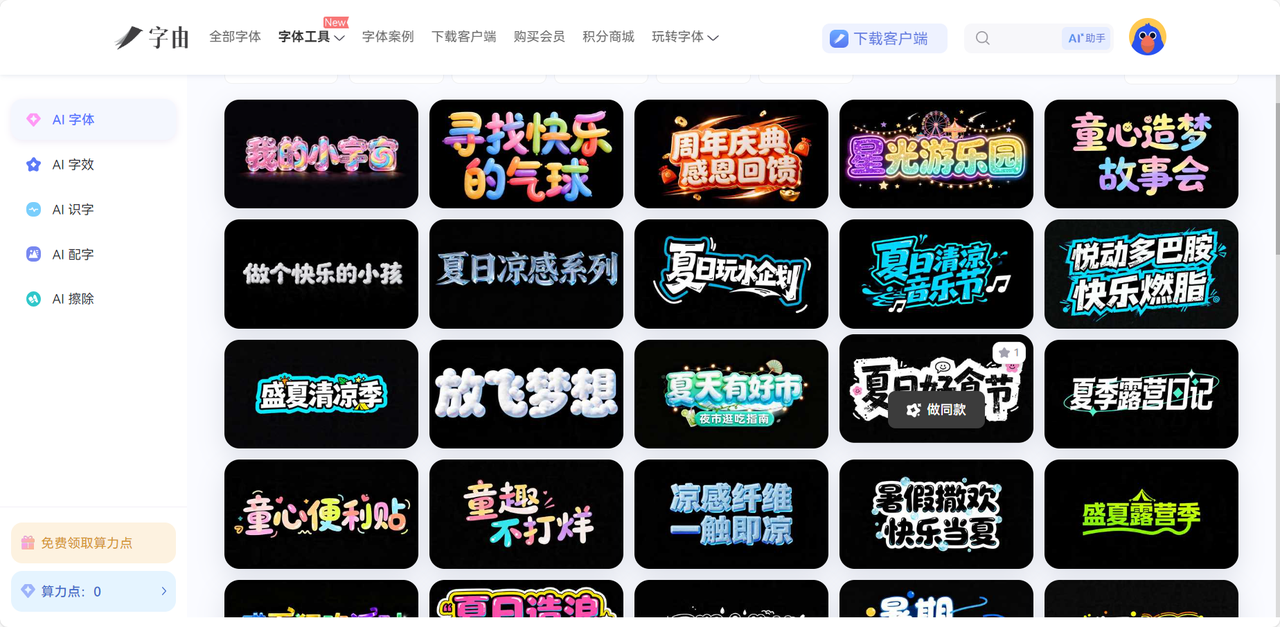
二、Canva
想必大家对于 Canva 都不陌生,它以丰富的模板资源和强大的设计功能而闻名,艺术字生成方面更是深受用户的喜爱。不同于文字类的生成工具,Canva 的艺术字生成是和设计模板深度融合的,也就是说,用户生成艺术字的时候还可以直接搭配背景、装饰元素等细节,一键就能获得完整的艺术字标题设计,适合用于海报设计行业。用户只需要在平台中搜索“艺术字标题”或对应的设计场景,Canva 会自动弹出大量的设计模板,很多模板都是跟随当下流行的设计趋势设计的哦,符合主流审美。生成的艺术字支持下载为 PNG、JPG、PDF 等多种格式,也可以直接分享到社交媒体平台,非常方便。不过需要注意一点,Canva 的部分热门模板和高级字体需要升级付费版才能解锁,但对于普通用户来说,免费模板已经足够覆盖日常需求,即使是第一次使用的新手,也能在几分钟内做出满意的高级感标题。
三、Adobe Express
Adobe Express 作为 Adobe 旗下的免费在线设计工具,艺术字生成功能专业且有设计感,因此也成为了很多设计师的必备工具。它不单单是提供文字的变形,而是从字体效果、质感优化、风格选择等多方面都做到了专业的水平,艺术字呈现效果非常细腻、高级、自然。用户进入官网后,在画布内添加文字,然后选择丰富的字体效果,包含渐变、发光、阴影、纹理、扭曲、描边等,不同效果之间可以叠加使用,有助于打造极具质感的艺术字效果。由于是 Adobe 下属的工具,平台上的字体库内还包含了大量的 Adobe 官方正版字体,用户可以直接选择,也可以上传自己的字体使用,满足不同风格的需求。对于熟悉 Photoshop 等软件的用户来说,操作逻辑都是类似的,上手非常轻松;对于新手来说,平台也提供了大量预设模板和教程,帮助用户快速掌握艺术字效果调整技巧。
四、PicMonkey
偏爱创意艺术字和趣味艺术字的小伙伴注意看!PicMonkey 是一款专门设计活泼创意艺术字效果的工具,生成的艺术字比较适合的用于社交媒体配图、动画封面等年轻用户较喜欢的场景里。用户进入该工具内,添加文字内容后就可以进入文字效果专区,除了基础的渐变、阴影效果,PicMonkey 还提供了文字弯曲、文字填充图片、动态效果等独特的功能,用户自由度很高,能快速生成极具创意和吸睛效果的艺术字。除此之外,PicMonkey 还有大量的贴纸、边框和背景素材,可以搭配艺术字一起使用哦。不过,该工具的免费版有一定的使用限制,导出的文件会带有平台水印,部分高级效果和素材需要付费才能用,大家可以体验过后自行斟酌一下。
五、Photopea
Photopea 是一个图片编辑工具,同样也能在线生成艺术字,而且能实现很多复杂的艺术字效果。简单来讲,Photopea 算是 Photoshop 的免费平替版,功能几乎都是一样的,而且还不用登录注册软件,在线就能用,实用性极强。用户通过图层样式就可以直接为文字添加艺术字效果,比如渐变、浮雕、发光等,还可以自由调整每个效果的参数,甚至可以为文字添加纹理和材质效果,选择很多,能生成的艺术字风格也很多!生成的字体支持导出为 PNG、JPG、PSD等多种格式,也可以直接保存为透明背景文件,方便在其他设计软件中使用。对于一些零基础用户来说,可能需要你稍微学一下才能上手,但是操作很简单,了解一些基础操作就能做出和专业软件媲美的艺术字效果。